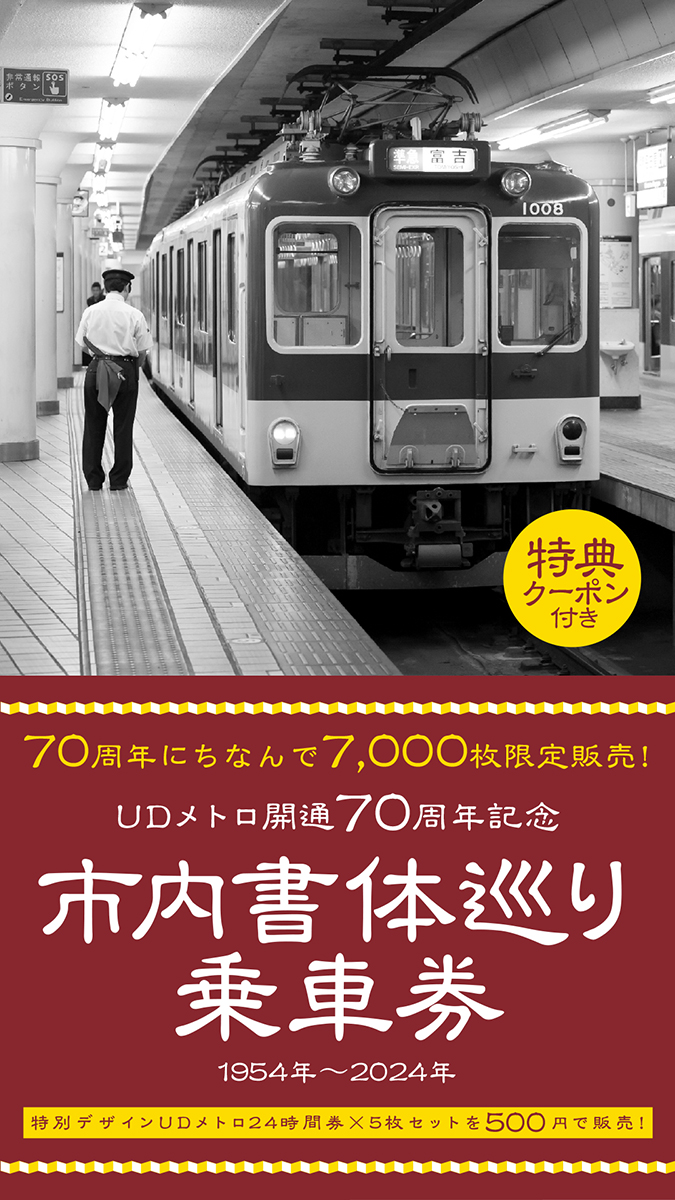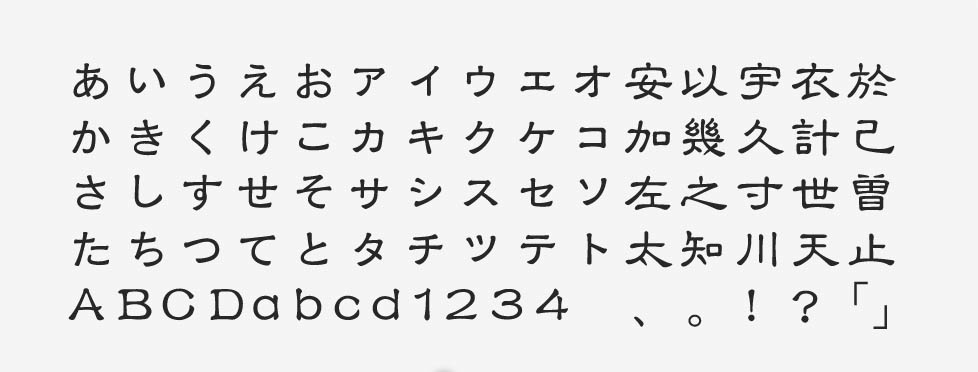
「花牡丹」について
TypeBankブランドの「伝統書体シリーズ」の1つで、漢字は台湾のArphic Typesで開発され、かな文字はタイプデザイナーの今田欣一氏がデザインを手掛けました。隷書の伝統的な佇まいを踏襲しながらも、新しい時代に対応できるようなデザインに仕上げられています。
「花牡丹」の特徴
隷書は波磔(はたく)と呼ばれるうねりのような筆勢が特徴ですが、花牡丹はそれを強調しすぎずに抑制をきかせてあります。また、かな文字は、同じく隷書に特有の平べったい扁平の字形も強調せず、風合いを損ねない程度に正方比率に整えられています。
これらのデザインにより、漢字・かな・英数字がなじんだ安定感のあるフォントです。全体的に字面は小さめで、品のある穏やかな雰囲気を感じさせます。
作例で使った花牡丹は、柔らかく、ぽってりして可愛らしいフォントです。同じ伝統書体シリーズの花胡蝶はエッジが利いていて格好良く、花蓮華は両者の特徴が共存したスタンダードな印象です。どのフォントも共通して「和」でレトロな印象なので、イメージに合わせて使い分けると良いでしょう。
書籍、絵本、ロゴ、印章、リーフレット、ポスター、商品パッケージ
「花牡丹」の書体情報